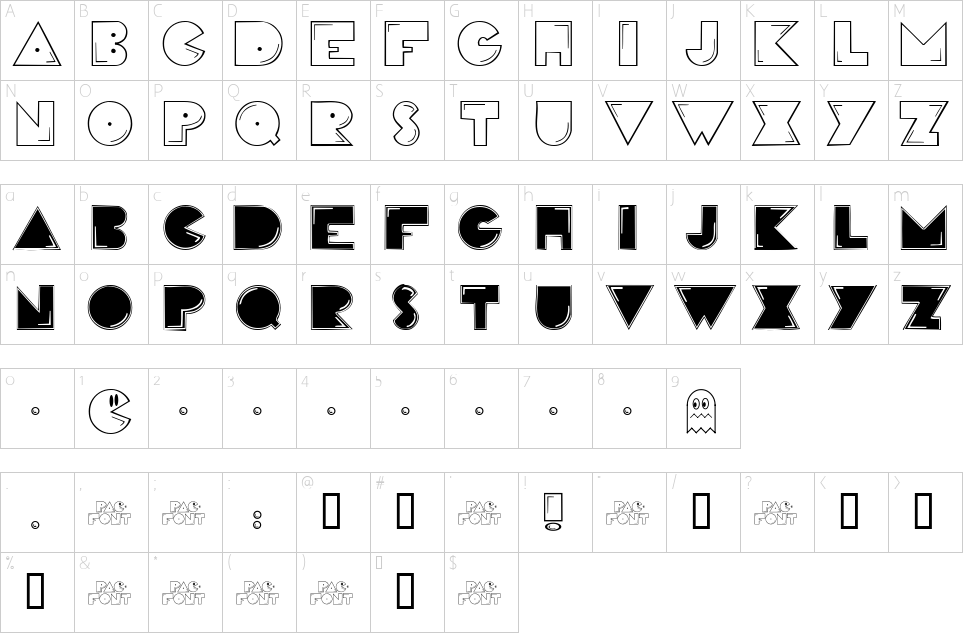
Descubra Pac Font, uma elegante fonte que se destaca tanto para projetos profissionais quanto para criações casuais. Desenhada por Fontalicious, esta font é versátil e possui um estilo minimalista que harmoniza perfeitamente com várias tipografias existentes. Se você está procurando uma fonte moderna e sofisticada que seja fácil de ler em qualquer dispositivo, Pac Font é a escolha certa. Com um design sólido e bem ponderado, esta font vem com uma ampla gama de opções de tamanho e estilo, garantindo que atenda às necessidades específicas de seus projetos. Com seu download gratuito, você pode adicionar esta estética moderna a qualquer projeto sem precisar se preocupar com compras extras ou licenças complexas. Seja para um website, cartazes publicitários, logotipos personalizados ou simplesmente textos em uma mensagem de e-mail, Pac Font traz seu toque único e elegante à sua criação. Neste momento, Pac Font já foi baixada mais de 107.410 vezes, o que reflete não apenas sua qualidade, mas também o crescente reconhecimento por parte dos designers do mundo inteiro. Experimente hoje mesmo a diferença que uma fonte como Pac Font pode fazer em seu trabalho.